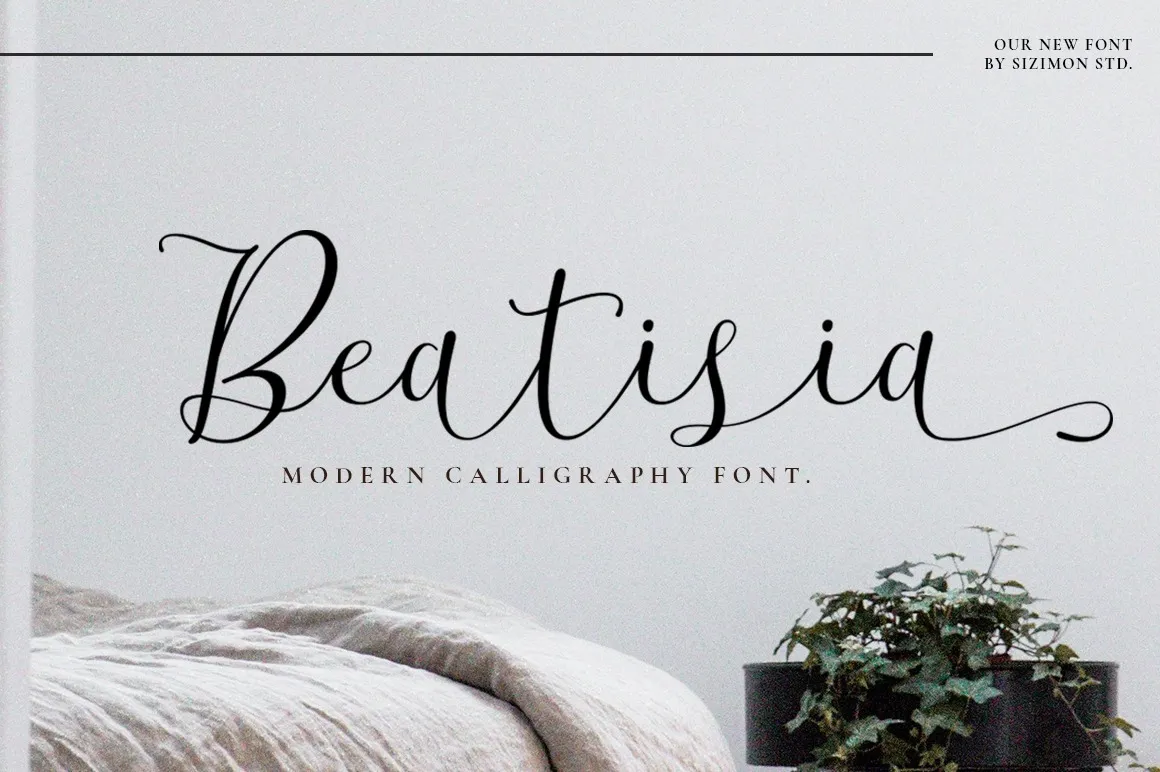
Beatisia é uma nova font criada pela equipe na 99designs que se destaca por sua simplicidade atraente. Inspirada em letras dançantes, Beatisia possui uma aparência suave e limpa, perfeitamente adaptável para um vasto leque de usos, desde cartões de convidados até menus, logotipos e selos de embalagem. Este script font é o ideal para qualquer evento ou aniversário que busque um estilo elegante e moderno, trazendo alegria aos designs com sua natureza suave e fluida. Seja você designer gráfico ou impressões em casa, Beatisia é uma escolha certeira para aqueles desejando adicionar um toque especial às suas criações.